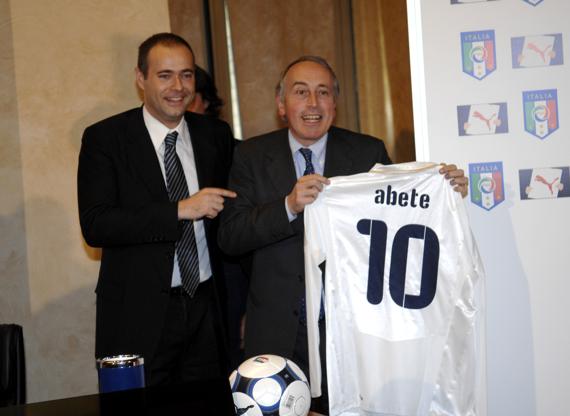
Bis jetzt folgende Team's:
-Deutschland
-Frankreich
-Griechenland
-Italien
-Kroatien
-Niederlande
-Österreich
-Schweiz
-Spanien
-Tschechien
-Türkei
Ich weiß nicht, was stimmt... aber Kakà 15 hat bei seinen Auswärtsfont ne andere Farbe^^ Einer muss es also falsch haben^^
Er hat zu dunkel, ich vll. etwas zu hell... Zahnlücke
BRASILIEN Home, Away/ Keeper
1. Bundesliga 07/08
..::FONTMAKER's Fonts::.. 1. Bundesliga 07/08